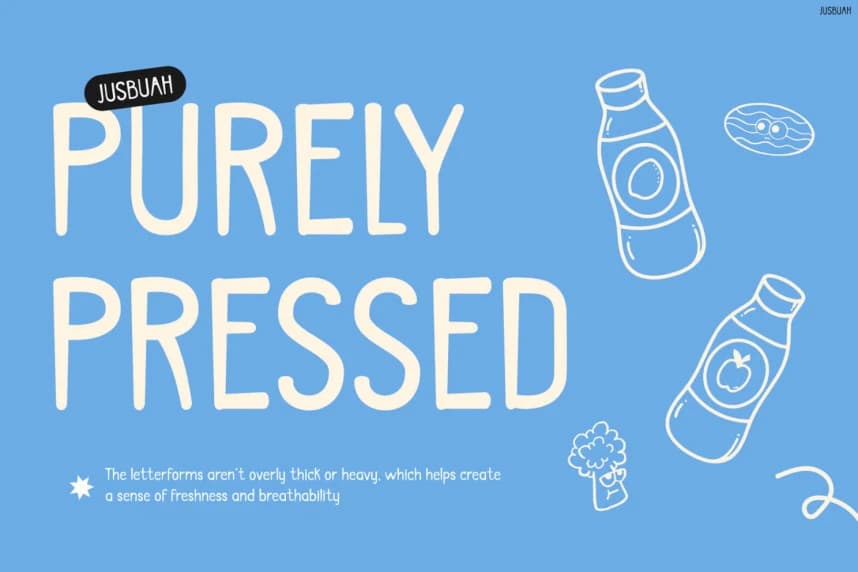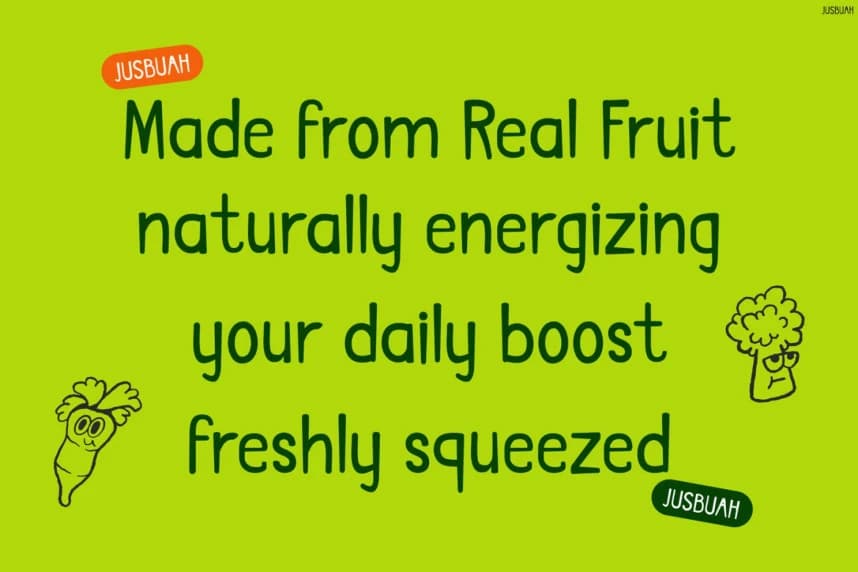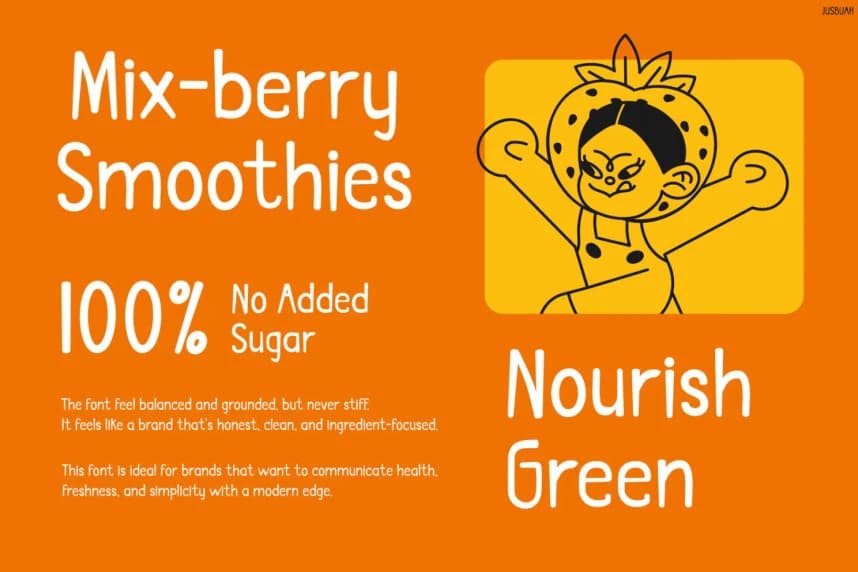
Jusbuah Neşeli Yazı Tipi
Jusbuah Playful Font, neşeli bir enerji patlaması sunar ve oyunbaz el çizimi stiliyle anında dikkat çeker. Ayrıca, yuvarlak ve hafif düzensiz şekilleri doğal, organik bir his yaratır ve meyvemsi bir tazeliği yansıtır.
Jusbuah Playful Font, neşeli bir enerji patlaması sunar ve eğlenceli, el ile çizilmiş stiliyle anında dikkat çeker. Ayrıca yuvarlak ve hafif düzensiz şekilleri, meyve tazeliğini yansıtan doğal, organik bir his yaratır.